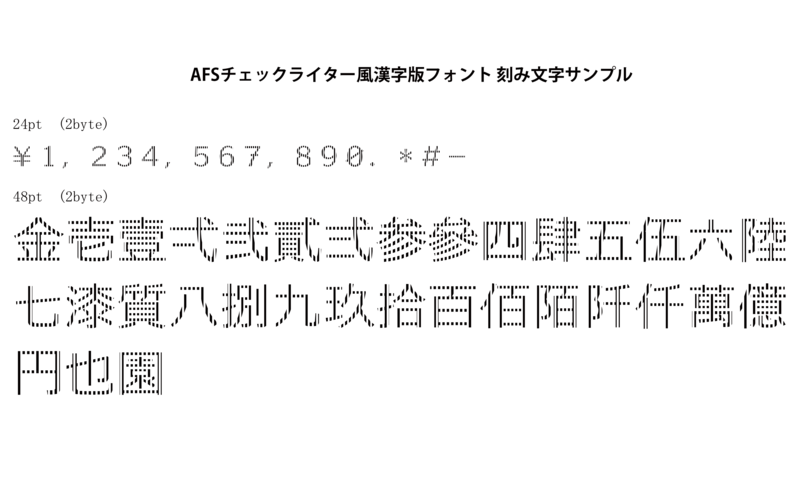
数字・一部記号・一部漢字
※日本語2byte刻み文字は以下が対象です。
「金壱壹弌弐貳弍参參四肆五伍六陸七漆質八捌九玖拾百佰陌阡仟萬億円也園」
※非漢字部(記号類)は、セキュリティ関連で有効な記号を集めました。
※刻み漢字以外はフォントデザイナー鈴木竹治氏「ドゥ・クラシックM」(JISX0208-1997)より許可を頂き複製しました。
日本語チェックライター風フォントは、基幹業務ソフトウェアを開発をされているIT企業様向け製品です。領収書、請求書向などの出力に最適なチェックライター風な刻み文字を搭載したアウトラインフォントです。